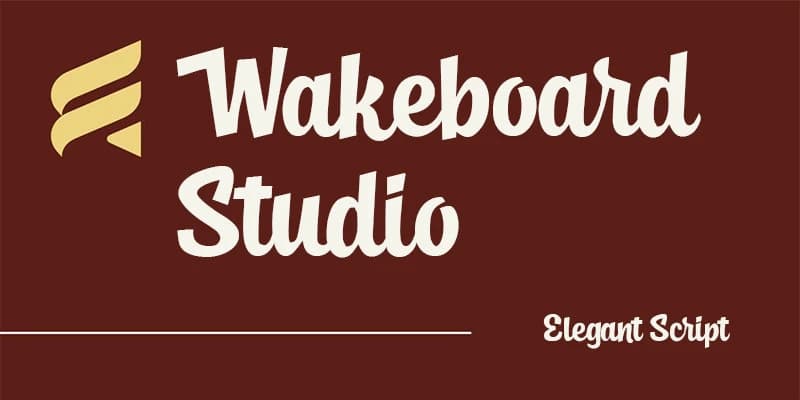
Wakeboard Studio Font
Wakeboard Studio Font, doğal, akışkan ve ifadeli bir his veren şık bir el yazısı script fontudur. Pürüzsüz, hafif düzensiz çizgileri gerçek el yazısını taklit eder ve bu yazı tipine gündelik ama modern ve yaratıcı bir görünüm kazandırır.
Wakeboard Studio Font, doğal, akıcı ve ifadeli bir his yakalayan şık bir el yazısı fontudur. Pürüzsüz, hafif düzensiz çizgileri gerçek el yazısını taklit eder ve bu yazı tipine sade ama modern ve yaratıcı bir görünüm kazandırır.